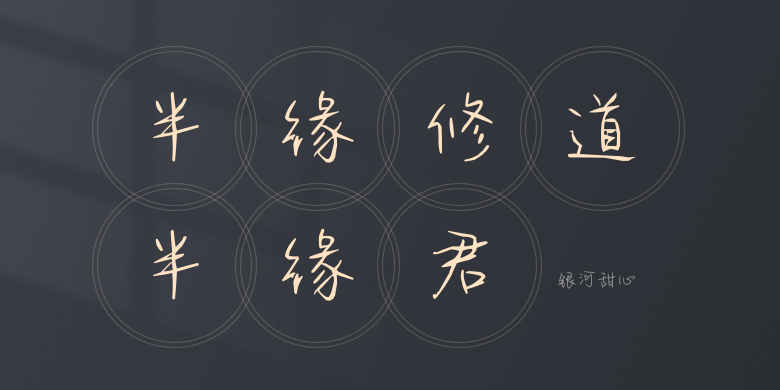
银河甜心
银河甜心,这款字体结构工整、笔画清晰,兼顾美观与易读性,适用于标题、正文、海报、包装、LOGO 等多种场景。字形优雅稳定,风格百搭耐看,适配日常排版与创意设计,让文字呈现更舒适、更具质感。银河甜心一笔一画,皆是细节,以均衡的比例、流畅的线条打造舒适视觉体验,字形端正大气,风格简约现代。无论是商业设计、品牌宣传还是日常排版,都能轻松驾驭,让文字更有格调与力量。银河甜心字体下载。